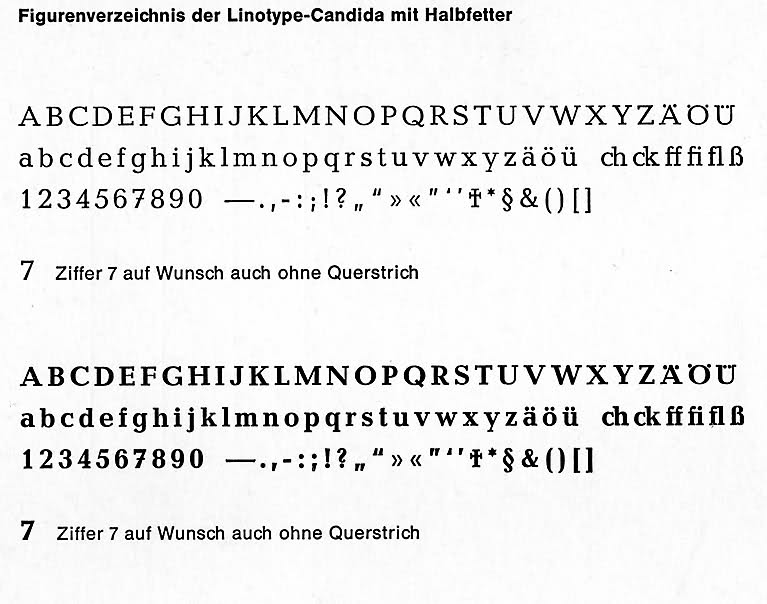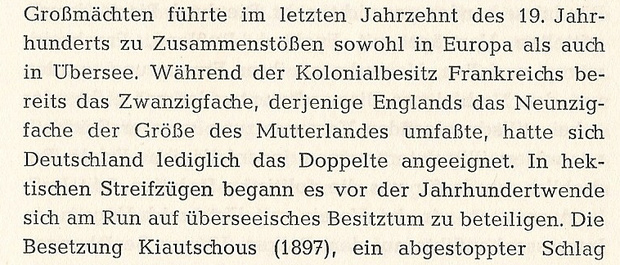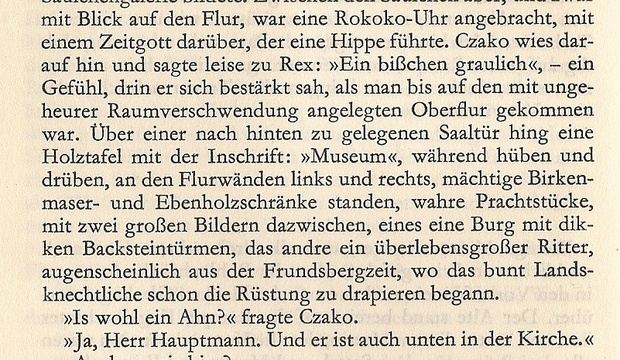
Borgis Garamond?
Ich finde diesen Font sehr oft in Büchern der 60/70er Jahre. Meist ist angegeben, dass sie aus der Borgis Garamond gesetzt wurde. Borgis bezeichnet meines Wissens den Schriftgrad. Gibt es diesen Font auch digitalisiert - besonders interessant sind die Umlaute und die Zahl 7.
Das ist eine schöne Schrift, gefällt mir. Sieht aber so gar nicht nach einer Garamond aus … :-?
Bei deinem Schriftmuster handelt es sich nicht um die Garamond sondern um die Candida.
Der Schriftgrad Borgis steht für 9 Punkt.
Borgis ist der Schriftgrad 9p. Mit einer Garamond oder einer anderen Renaissance-Antiqua hat die abgebildete Schrift nichts zu tun, erinnert eher an Schadow, Candida, Volta, also eine Egyptienne. Bücher sollte man damit kaum setzen.
Es gibt zwei digitale Candida mit dem Ü und der 7 des Beispiels. (Tschichold hat sich übrigens über den Querstrich in der 7 grundsätzlich geärgert, seit ich das las, schreibe ich handschriftlich Mediävalziffern ohne durchgestrichene Versal-7.)
Dankesehr! Der abgebildete Text ist sicherlich Maschinensatz, so schlecht würde kein Handsetzer ausschließen. Vielleicht gabs noch eine andere Handsatzvariante, oder im Bleisatz-Magazin Rheinland (obiger Link) haben wir die halbfette Schrift falsch ausgezeichnet übernommen.
Vielen Dank euch allen! Ich habe mir bisher bei Linotype und Adobe die vorhandenen Candida angeschaut, leider hat keine die alten Umlaute. Hat jemand noch eine Alternative?
Die von URW++ hat ein Ü, was in die Richtung geht:
Ich habe noch einmal die ursprünglich gemeinte "Borgis Garamond" gescannt. Im Impressum ist verzeichnet "Monotype Borgis Garamond". Kennt jemand eine diesem Schriftbild identische Garamond als Digitalisat?
Exakt digitalisierte Bleisatzschriften können im Offset nicht dieselbe Wirkung haben, weil die Quetschränder und die leichte Dreidimensionalität durch die Prägung der Bleischriften ihren Duktus beeinflussen; auch die Unregelmäßigkeiten, die im Buchdruck auftreten wie das Zulaufen von Punzen mit Farbe, verleihen der Schrift eine Bewegung, die sie im Offset nicht haben kann. Im Offset wirken Bleischriften immer schwächer, deshalb sollte für Offset besser eine verbesserte Schrift verwendet werden. Gerade für die Renaissance-Antiqua besteht eine ausgezeichnete Auswahl, Arno und Minion beispielsweise, aber es gibt auch gute Garamonds.
Die Monotype-Garamond auf dem Bild ist gut gesetzt, aber eben ohne Randausgleich, das konnte zwar Gutenberg im Handsatz, aber auf der Monotype wurde es nicht gemacht. Und die Garamond hat recht kurze Unterlängen und zu große Versalien, ist also auch keine Schönheit, die es zu erhalten gelte.
Borgis spielt keine Rolle. Auf meinem Bildschirm sehe ich eher Cicero als Borgis, also eher 12p als 9, und als Didot-Punkte, nicht Pica, wie sie heute digital verwendet werden. Wenn man den Schriftgrad kopieren will, muß man Zeichen auf Zeile auszählen (spätere Ergänzung: Achtung, Bleisatz läuft weiter als digitaler Satz!) und das digital anwenden und Ausdruck und Buchseite übereinanderlegen. Für digitale Schriften gilt noch stärker als für Blei, daß Schriftgrade eben nur Kegel betreffen und nicht Buchstaben.
Ich finde diesen Font sehr oft in Büchern der 60/70er Jahre. Meist ist angegeben, dass sie aus der Borgis Garamond gesetzt wurde. Borgis bezeichnet meines Wissens den Schriftgrad.
Wenn Borgis Garmond angegeben wäre, würde ich als Schriftsetzer aus dem Bleisatz diese Information möglicherweise auch als 9-Punkt Schrift auf einem 10-Punkt Schriftkegel werten mögen («Setz das mal in Borgis auf Garmond!»). Ich erinnere mich aber auch gut daran, dass nicht nur ich "Garmond" während der ganzen Lehrzeit ständig mit "Garamond" verwechselte. In der Schweiz wurden uns Lehrlingen die Schriftgrössen im Bleisatz wie folgt beigebracht (um 1975):
2˙ = Nonplusultra (nur auf 6-Punkt Kegel)
3˙ = Brillant (nur auf 6-Punkt Kegel)
4˙ = Diamant (nur auf 6-Punkt Kegel)
5˙ = Perl (nur auf 6-Punkt Kegel)
6˙ = Nonpareille
6½˙ = Insertio
7˙ = Kolonel
8˙ = Petit
9˙ = Borgis (auch Bourgeois)
10˙ = Garmond (auch Korpus)
11˙ = Rheinländer
12˙ = Cicero
14˙ = Mittel
16˙ = Tertia
18˙ = Paragon
20˙ = Text
24˙ = 2 Cicero (auch Doppelcicero)
28˙ = Doppelmittel
36˙ = 3 Cicero
48˙ = 4 Cicero
Aber Achtung: ich habe diese Angaben soeben aus einem meiner eigenen Notizbücher der Lehrzeit abgeschrieben. Das bedeutet, dass ich das absolut ohne jeglichen Anspruch auf Gewähr etceterapipapo hier wiedergebe.
Norbert, die Kegelangaben für die Grade unterhalb Nonpareille beziehen sich auf den Druckereibestand. Es wurde von Gießereien angeboten und gibt auch in meiner Werkstatt eine 4p- und eine 5p-Schrift auf entsprechendem Kegel.
Darf ich die Erinnerung berichtigen? Wenn man Borgis auf Korpus setzt, bedeutet das, eine 9p-Schrift auf einem Borgiskegel mit einem Punkt zu durchschießen. Die Satzanweisung heißt beispielsweise: 20/9/10, das bedeutet 5 Konkordanz Satzbreite und 9p-Schrift mit einem Punkt (umgangssprachlich eine Achtel) Durchschuß. Die 9p-Schrift auf 10p-Kegel würde hier eher nicht verwendet werden, weil der Satz selbst dann kompreß wäre und schwer zu verarbeiten.